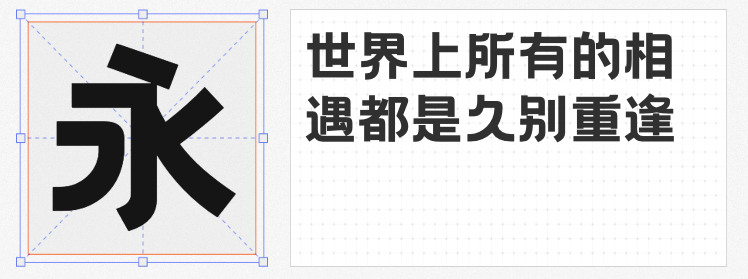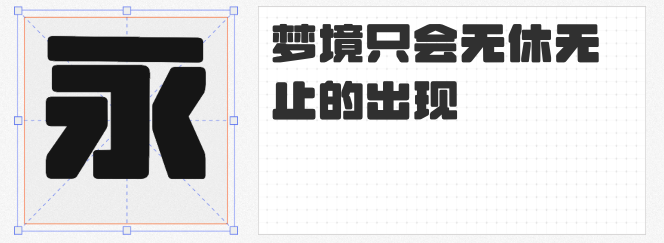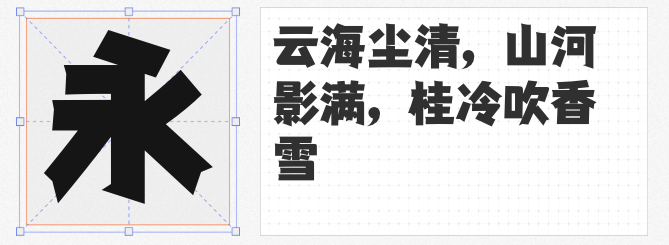
在商业设计中,粗黑体以其强烈的视觉存在感和现代感,常被用于标题、海报等需要突出重点的场景。以下四款免费商用字体兼具力量感与设计巧思,且支持中文、英文及标点混排,助你打造醒目且不失精致的视觉作品。
1. 仓耳与墨 W05
这款字体以篆刻艺术为灵感,将“刀意”融入笔画,模拟刻刀的利落切痕,赋予字体独特的金属质感。转折处采用圆润处理,形成“内方外圆”的视觉对比,既保留传统篆刻的厚重,又避免尖锐感。配套的英文与标点延续了中文设计语言,混排时风格高度统一,适合科技、运动类品牌的视觉表达。
2. 字由文艺黑
字由文艺黑突破传统黑体的方正框架,通过流畅的艺术弧线重构字形结构。笔画粗细对比柔和,字面饱满而不显臃肿,在保持现代感的同时增添一丝优雅气质。其方正骨架与动态弧线的结合,使文字在海报、包装等场景中既能传递力量,又能展现细腻的视觉层次。
3. 千图厚黑体
千图厚黑体以宽扁字面构建厚重形态,笔画末端加入微妙倒角,削弱粗黑体的压迫感。中宫紧凑的设计让文字组合时更具凝聚力,笔画细节的修饰则提升了字体的设计感。无论是活动海报标题还是品牌主视觉,这款字体都能以“粗中有细”的特质平衡视觉冲击与审美需求。
4. 荆南缘默体
荆南缘默体以“占满扁长方形”为设计目标,最大化利用版面空间。笔画粗细均匀,字形简洁有力,尤其适合需要快速抓取视线的场景,如店招、公交站广告或短视频封面。其极简风格与高辨识度,使其成为商业宣传中“一锤定音”的标题首选。